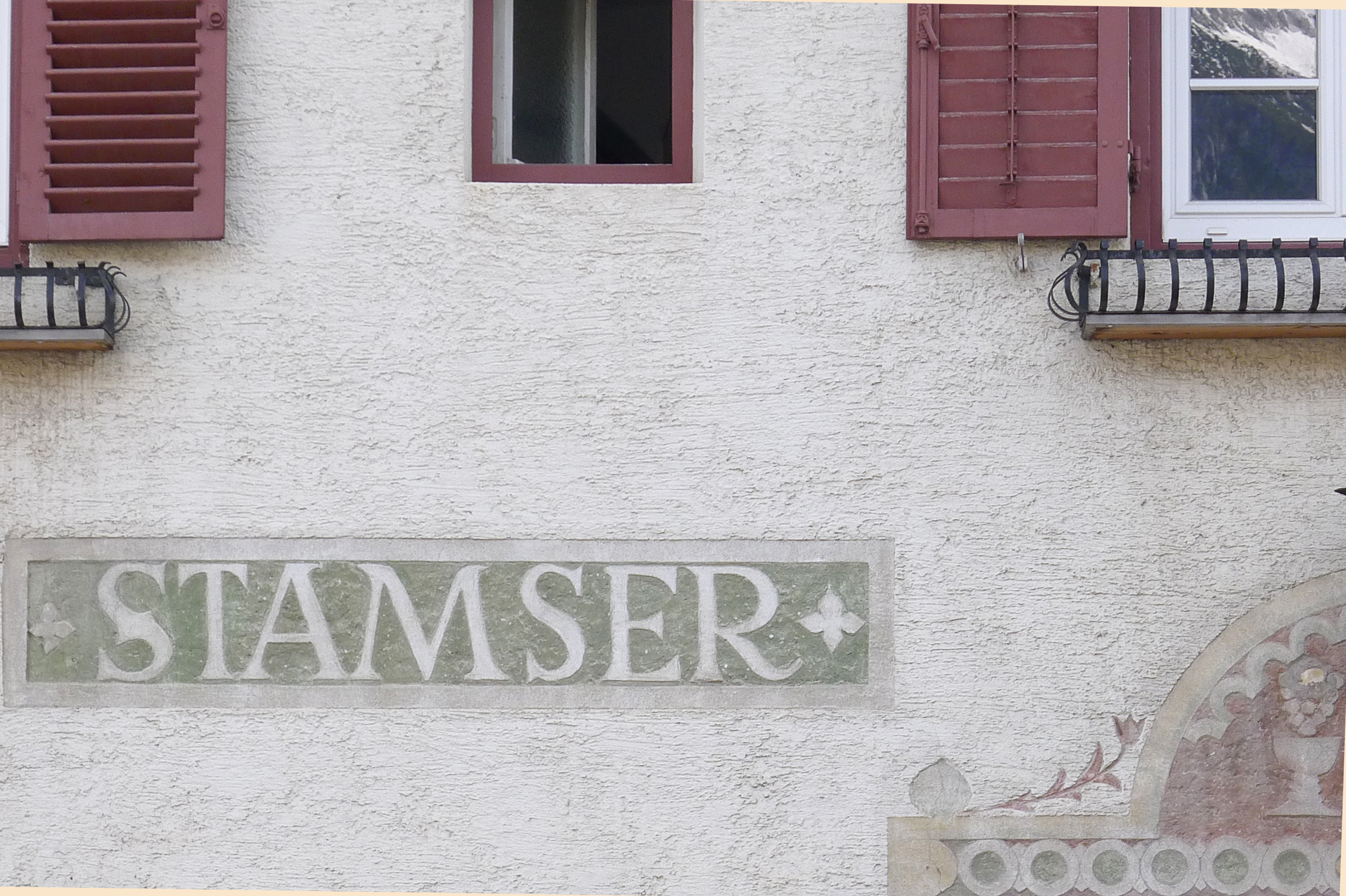
Stamser WEI SRAUM Designforum Tirol, Absam/Tirol # 25/04/17 Categories: Serif Tags: Sgaffito, Fassadenschrift, Gasthaus Sgraffito an einem ehemaligen Wirtshaus östlich von Innsbruck.So schön dezent und passen in die Fassade eingefügt! 336 Likes